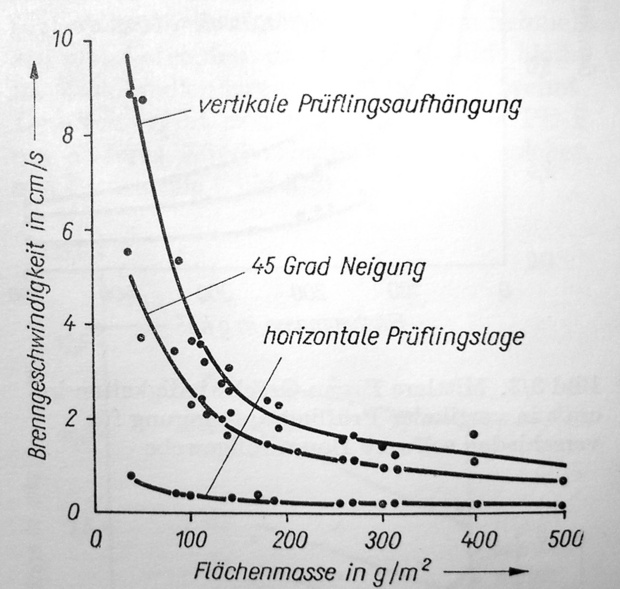
"Vintage DIN"-Schrift; rounded, condensed, italic; (DDR-Typo?).
habe heute mal ein Identifizierungsgesuch.
Bin in einem DDR-Lehrbuch (1981) auf diese Schrift gestoßen. Ich vermute inzwischen , dass es eine damalige TGL-genormte Schrift ist. Hier erst einmal ein paar Bilchen:
Sie sieht der "heutigen" DIN16/17 änhlich, ist bloß zusätzlich noch schräggestellt und condensed.
Das "DDR-Pendant" dazu, wäre rein theoretisch die TGL 0-16, sie ist schräggestellt und sogar eng, kommt ihr ziemlich nahe - doch trifft auch nicht 100%ig zu.
Die "next Generation" wäre dann die TGL 31034, doch diese entfernt sich schon wieder viel zu sehr vom Schriftbild; sie ist es also auch nicht.
Nun meine Frage(n):
Kann es sein, dass die Abbildungen in diesem Lehrbuch vom Verfasser mit einer Schablone beschriftet wurden und es damals eine gewisse "Varianz" bei der Fertigung selbiger gab, sodass die Glyphen nirgends wirklich gleich aussehen konnten?
Oder gibt es hier doch noch eine andere solche Normschrift?
Man beachte das "f" und das "z"; sie sind definitiv etwas anders, als die aufgestöberte TGL 0-16. Vllt hat ja auch der TGL-0-16-Ersteller ungenau gearbeitet. Weiß evtl. jemand, wie die echte TGL 0-16 aussah, gibt es davon irgendwie irgendwo Bilder, dass man einmal vergleichen könnte? Besonders da es von der TGL 0-16 scheinbar quasi zwei Versionen gab: eine frühe, dickere und eine spätere etwas dünnere in der Linienstärke. Vllt ist es ja diese - habe nur leider keinerelei Referenzbilder dafür.
Falls hier also jemand tiefes Insiderwissen hat, dann immer raus damit! ;)
Das ist handgeschrieben vom Technischen Zeichner. Schrift innerhalb solcher Graphiken konnte nicht ohne weiteres gesetzt werden, die Graphik war ja z. B. eine Zinkätzung, die auf Holz aufgeklotzt oder mit Blei hintergossen war. Um die Schrift setzen zu können, hätte man den Raum dafür ausfräsen müssen, oder man hätte das in mehreren Reproschritten ineinandermontiert. Also war es das einfachste, die Schrift gleich mit zeichnen zu lassen.
Würdest du deine Kinnlade wieder hochklappen, könntest du dich lockern und mit den Schreibübungen beginnen:
Oder du kaufst dir eine der früher in technischen (Zeichner-)Berufen weit verbreiteten Schreibschablonen:
Das konnte eine Freundin damals™ auch … sie hat Technisches Zeichnen noch von Hand gelernt, da war "freies DIN-Schreiben" ganz normal. Keiner hat (außer anfänglich) zur Schablone gegriffen, das hätte viel zu lang gedauert.
Würdest du deine Kinnlade wieder hochklappen, könntest du dich lockern und mit den Schreibübungen beginnen [...]
Das konnte eine Freundin damals™ auch … sie hat Technisches Zeichnen noch von Hand gelernt, da war "freies DIN-Schreiben" ganz normal. Keiner hat (außer anfänglich) zur Schablone gegriffen, das hätte viel zu lang gedauert.
:kinnladewiederhochklapp: Das ist aber echt ganz schön sauber und regelmäßig ...! :-o Was man sich nicht alles antrainieren kann ... :-?
Für ein Lehrbuch mag das stimmen, in den wissenschaftlichen Journalen wurden die Graphen von den Wissenschaftlern aber oftmals selber angefertigt. Wenn die Uni keine Repro-Abteilung hatte, dann wurde das durchaus per Schablone gemacht. Ich kenne viele ältere Kollegen, die das genau so selber gemacht haben. Die haben natürlich nicht die nötige Übung um das freihändig zu erledigen.
Sieht der dargestellten Zeichnung aber trotzdem frappierend ähnlich. :nicken:
Meine Altersgenossen, die in den 90ern die HTL absolviert haben, durften in technisch Zeichnen auch die Normschrift lernen, mit dem Ziel, eine derartige Regelmäßigkeit zu erreichen.